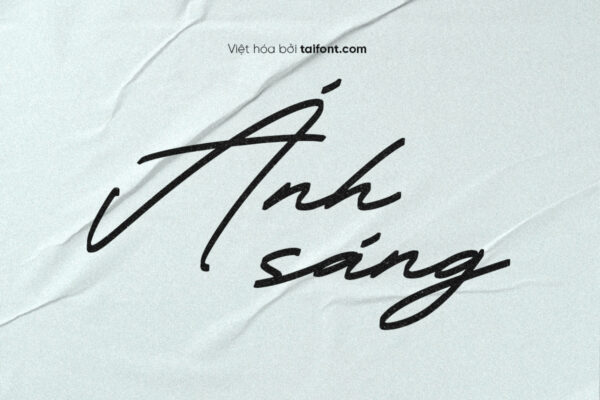
Tên font: Font việt hóa MJ Fuego
Font này chưa có dấu nên đã được tạo và font đã được thêm cách đánh bàn phím ra gly. Hiện tại có gly chữ thường là “d f g h j l p s v r đ ” và vài gly trang trí.